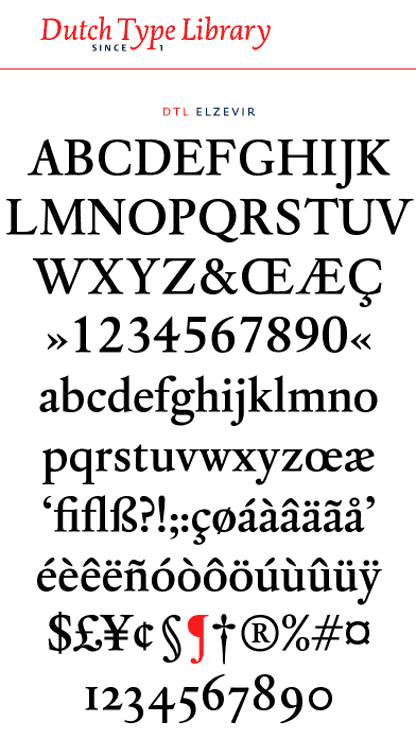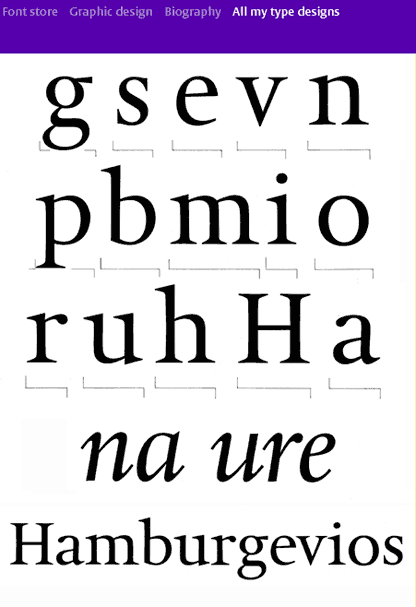
Custodia | plagiat or not plagiat | Jonathan’s answer to Our Type
En ce qui concerne les polices de caractères, c’est une histoire très compliqué. (Suite de la chronique: typographie introuvable)
En droit, l’alphabet, la base de tous les typos en quelque sorte, est un bien commun et non déposable, et donc pas protégable. Les polices de caractères sont même exclues, de manière explicite, de la plupart des législations sur la protection intellectuelle.
Les seuls éléments protégables étaient donc que le nom de la police, et non pas sa forme. Les exceptions étant les caractères *historiques* [garamond, bodoni, baskerville, caslon, scotch, et autres] dont le nom est antérieur à la période contemporaine, et donc, si un dépot avait existé à un moment, il serait tombé depuis longtemps. En fait ce n’est qu’avec l’arrivée des polices numériques qu’une protection est apparu, car les fontes sont assimilées [à tort ou à raison] à des logiciels, et bénéficient de la même protection intellectuelle et industrielle que n’importe quel autre logiciel.
Dans ce cas, même si, en tant que typophile [amateur ou professionnel], nous voyons clairement des filiations plus ou moins légitimes entre polices de différentes fonderies, il est difficile de parler de plagiat, un terme à la fois chargé et juridique, en dehors d’un cadre juridique pouvant donner lieu à ce *délit*. D’ailleurs, j’ai plus souvent entendu des typographes parler de *pompage* que de plagiat. C’est-à-dire, un dessinateur travaillant en dehors d’un strict *revival* va parfois *pomper* le travail d’un autre. Et dans ce cas, si la loi ne lui donne pas tort, très souvent les murmures de confrères vont le condammer plus sévèrement qu’aucune cour de justice.
Justement, le cas des *revival* est un phénomène intéressant à mettre à côté de la notion de plagiat. On aime à penser que tous les revivals sont des oeuvres *pures*, libre des basses considérations. Mais même si beaucoup de revivals sont des réinterprétations talentueuses de figures connus [un peu comme ta comparaison entre les interprétations de Bach, et des formes de différentes Garaldes], beaucoup sont des prestations de commande baclées, histoire d’être présent dans le marché. Je garde à l’esprit le nombre incalculable d’interprétations du Futura qui sont arrivées sur le marché américain avant l’arrivée *officielle* de cette police. Et pour combien de *Metro* de Dwiggins [un dessinateur pour qui j’ai beaucoup d’affection], qui y a fait oeuvre de création à l’intérieur des contraintes de ces nouvelles sans serifs de forme géométrique [sans être capable de cacher sa préférence personnelle pour les sans serifs humanistes, et ça se voit très clairement dans son dessin], il existe des *copies* serviles et mal dans leur peau, tel Spartan…
Dans le cas du Custodia, je vais prendre un autre chemin et présenter l’Elzevir medium de DTL « http://www.dutchtypelibrary.nl/ElzevirMedium.html« . Il s’agit d’un revival de *Van Dijck* clairement assumé dans la doumentation sur le site. Et cela ne pose pas de problème, Van Dijck étant mort depuis plus de 300 ans. DTL explique ensuite le choix, le pourquoi, le cheminement. Mais plutôt que de lui donner le nom de *New Van Dijck*, ils ont choisit de l’appeler *Elzevir*, un nom très attaché à la typo néerlandaise.
De manière semblable, *Hollander* de Gerard Unger
*http://www.gerardunger.com/allmytypedesigns/allmytypedesigns06.html* affiche lui aussi sa filiation avec Van Dijck, dans sa documentation, tout en ayant, comme DTL, choisit un nom plus neutre.
Le *Van Dijck* de Monotype , bien sûr, affiche clairement sa couleur. Et c’est peut-être à cause de son existence que DTL et Unger ont choisit de ne pas suivre le chemin du *Van Dijck Neue* pour leurs interprétations.
Ce qui est curieux sur le site d’OurType est que il n’y a pratiquement pas de mention de cette filiation. Il est indiqué seulement:
» A single-weight roman, with italic and matching small caps, with a seventeenth-century flavour. It was made in 2002 for use in the publications of the Custodia Foundation. Custodia 17 is the first typeface to join the OurType Classics collection.
Lisant entre les lignes — un ton 17e siècle ? — on peut comprendre une allusion à Van Dijck, mais il n’y a rien d’explicite. Il est probable que pour Fred Smeijers, cette filiation est claire comme de l’eau de roche, et non seulement pour lui, mais aussi pour son public [j’ai été frappé lors d’une visite au Pays-Bas par le souci et la sensibilité typographique tout autour de moi, et il est probablement que le pays possède encore une culture typographique que la France semble avoir perdu] ou bien c’est peut être que l’on perçoit mal ce qui est proche de soi tous les jours… et qui n’aurait donc pas besoin d’être plus explicite. Mais on peut légitimement se poser la question.
1. peter gabor dit :
oui merci pour vos encouragements.
Au fond la question est de savoir qui est véritablement trompé. Pour moi c’est le consommateur! Lorsqu’un de nos experts de l’ATypI s’y confond lui-même comment voulez-vous qu’un jeune DA qui a séché les cours de typo durant ses études ;-) puisse faire la différence entre le Van Dyck de Monotype et le Custodia d’OurType.
Ce faisant le site marchand d’OurType est très touchy, et donne vraiment envie d’acheter. Alors le jeune DA se tourne vers son acheteur au sein de l’Agence qui l’emploie et celui-ci y connaît encore moins…! S’il savait que les deux typos sont aussi ressemblantes, peut-être qu’il y réfléchirait à deux fois avant de débloquer l’opération d’achat.
La solution? une agence internationale de la typographie, neutre et non aligné qui tiendrait à jour une liste en Wysywyg de toutes les fontes disponibles dans le monde, classées par familles, par ressemblances et par origines afin de donner aux consommateurs un véritable outil de décision qui éviterait que l’on se retrouve sur une même machine avec des centaines de caractères qui font double emploi. Cela permettrait de libérer les décisions d’investissement pour de vraies créations uniques et novatrices. (Pure utopie je sais ;-)